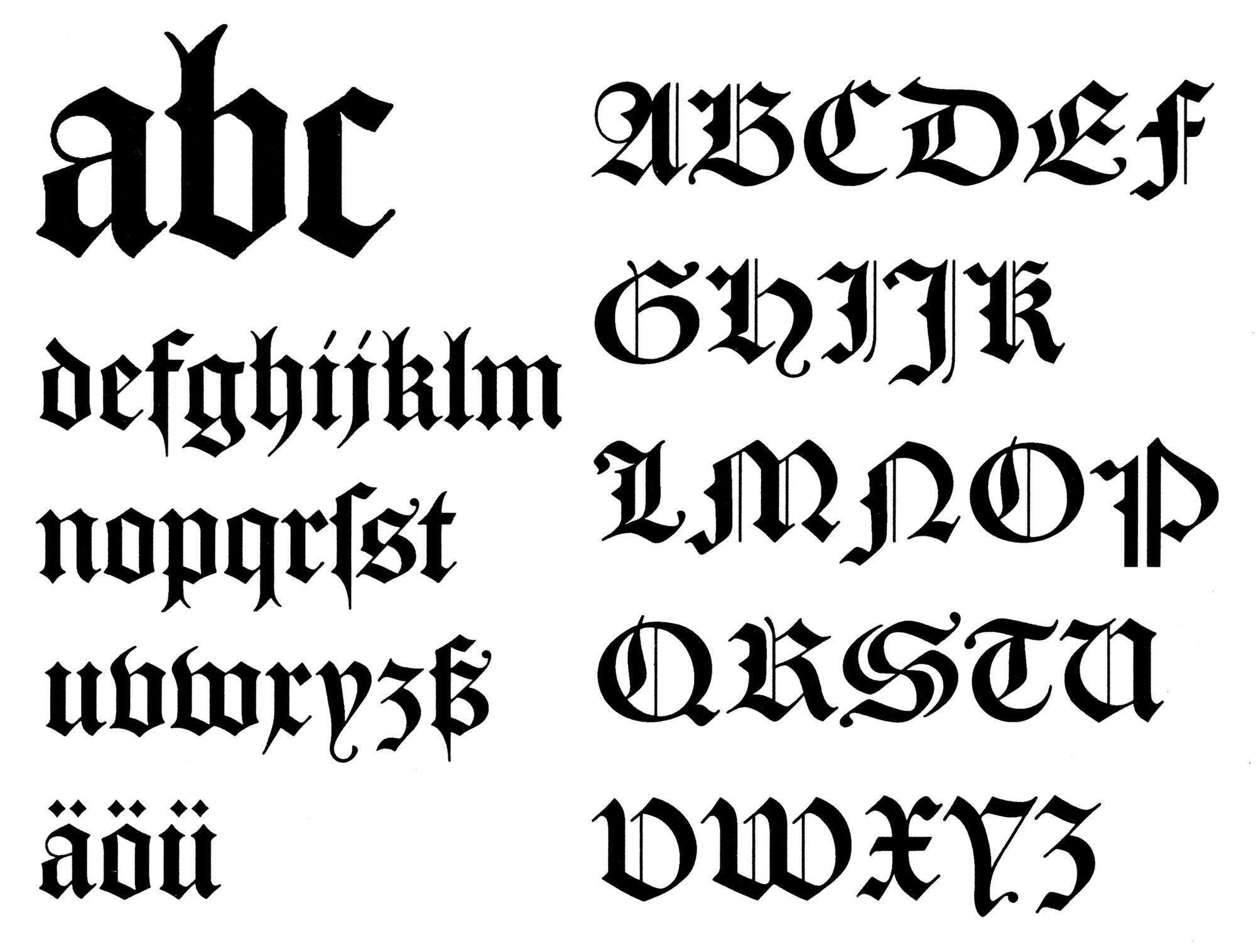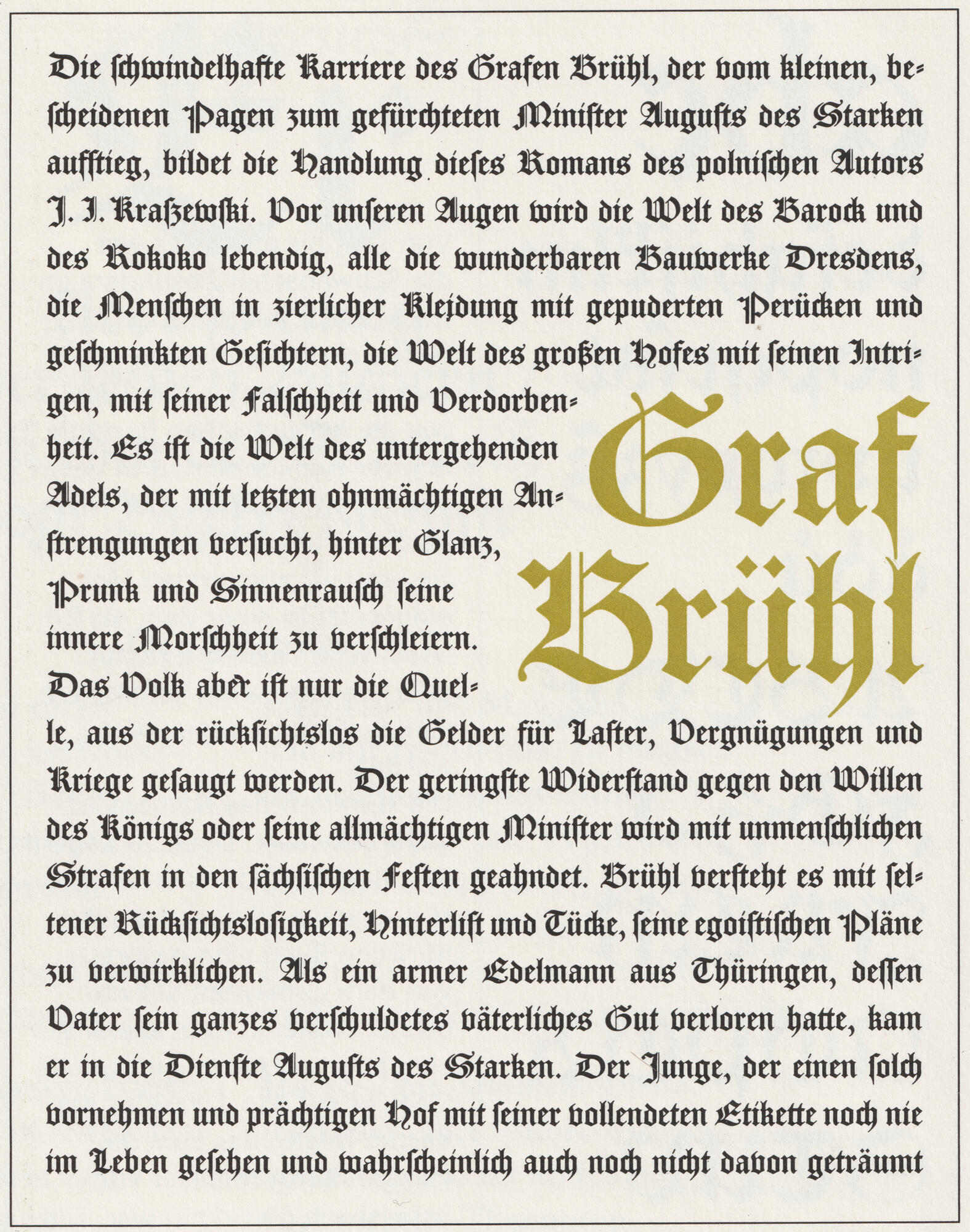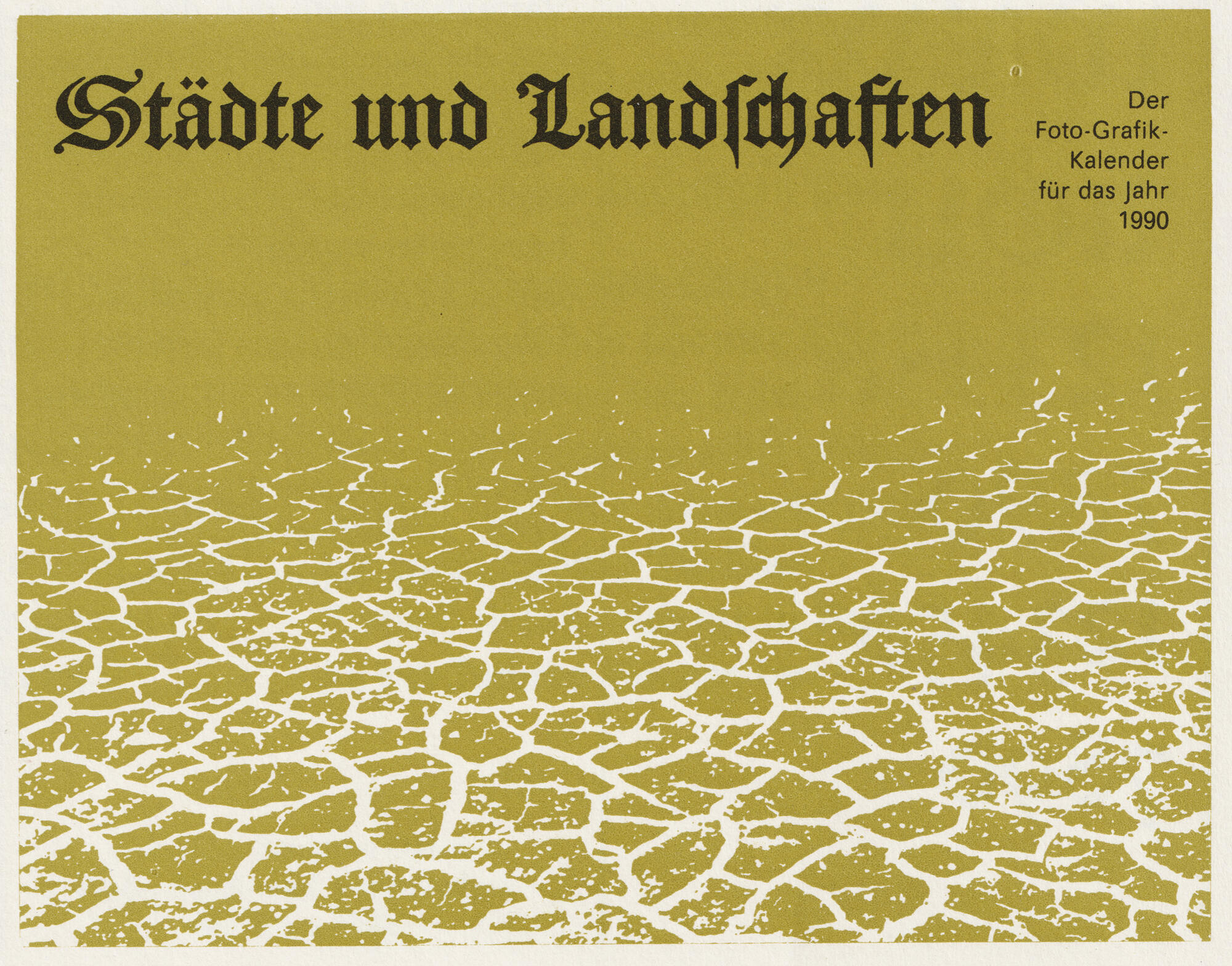
Die Fotosatz-Replik der englischen gotischen Schrift wurde von Erhard Kaiser künstlerisch betreut und erschien in den 1980er-Jahren über Typoart. Eine digitale Version einem Schaugrößenschnitt wurde über Elsner+Flake verfügbar gemacht.